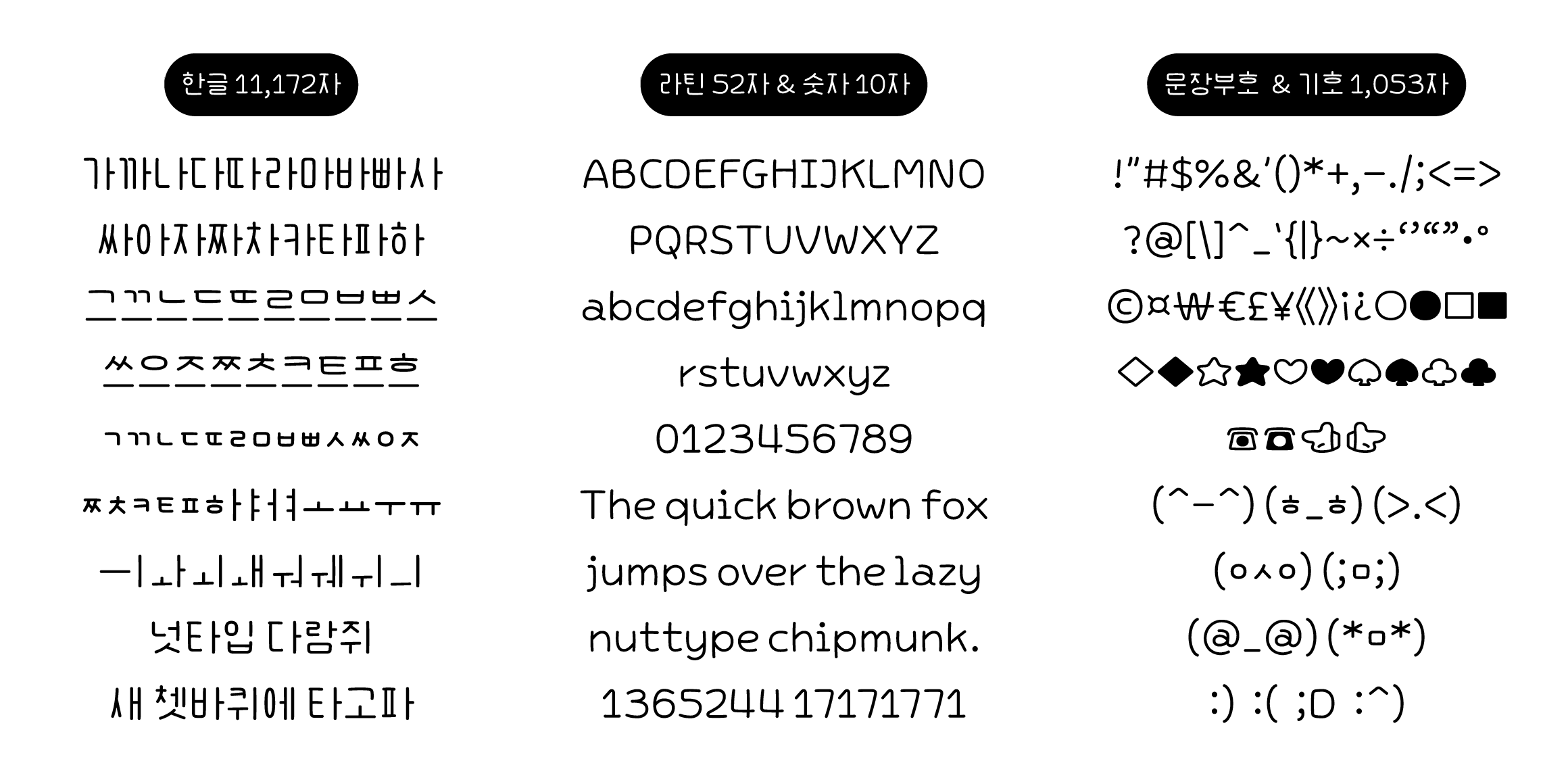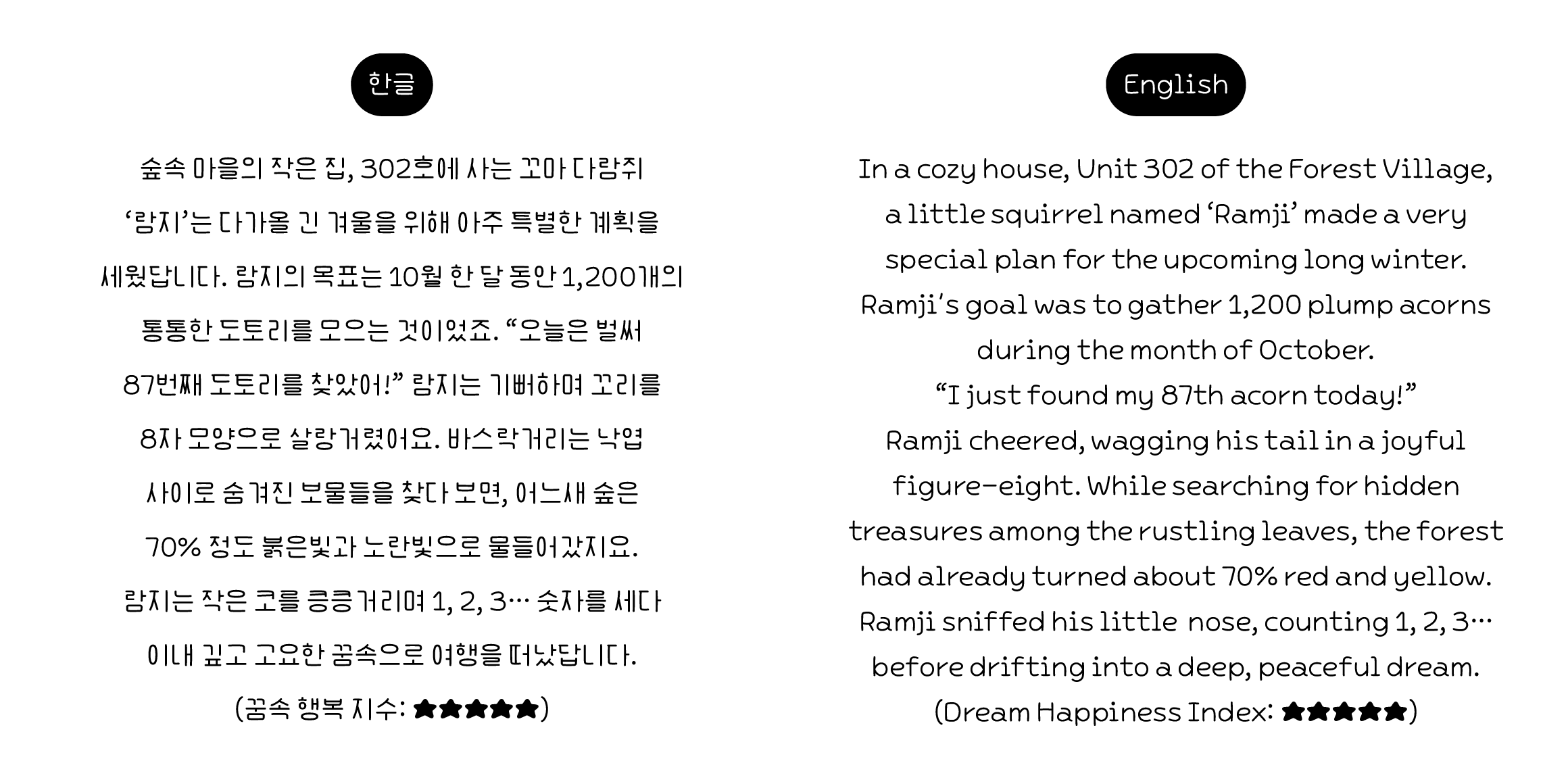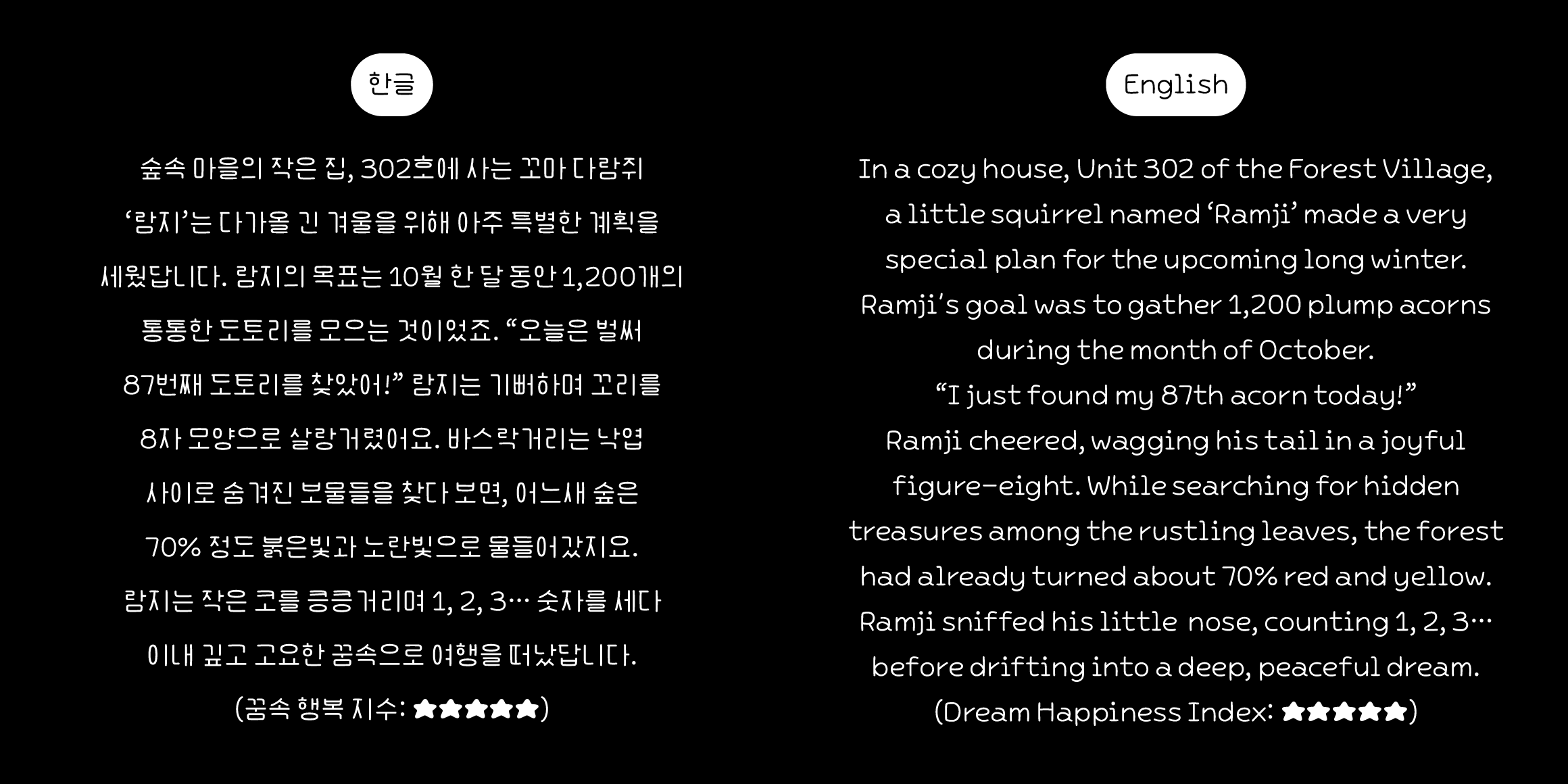
nut 베이비람지
Nuttype
nut 베이비람지 font in use
아, 가라고요ㅡㅡ! 아가라고요>ㅁ사춘기가 온 건지, 안 온 건지. 도무지 정체를 파악할 수 없는 혼돈의 다람쥐, 베이비람지.
질풍노도의 시기인가 싶다가도 금세 무장해제 미소를 발사하는 이 구역의 변덕쟁이!
혼자 있고 싶다며 시크하게 등을 돌리다가도, 막상 멀어지려 하면 “나 아가인데 혼자 둘 거야?”라며 소매를 붙잡는 마성의 소유자다.